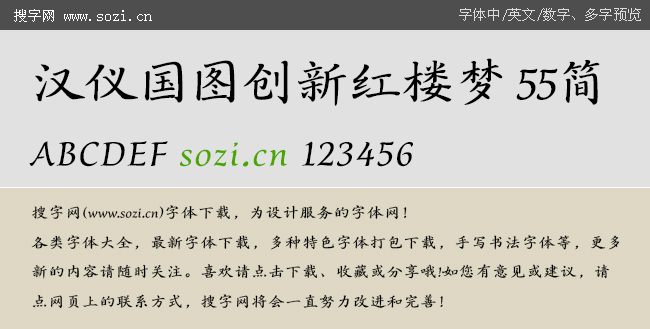
漢儀國圖創(chuàng)新紅樓夢 55簡
搜字網(wǎng)給大家提供一款漢儀國圖創(chuàng)新紅樓夢 55簡中文字體下載,漢儀國圖創(chuàng)新紅樓夢字體家族是一套藝術(shù)楷體字體,字體共擁有五款字重,字體簡潔大方,整體效果非常不錯。適用于畫冊設(shè)計(jì)、海報(bào)設(shè)計(jì)、包裝設(shè)計(jì)等場合使用。(本字體為個人非商用版,如需要商用請聯(lián)系漢儀公司購買版權(quán))
- 風(fēng)格類別: 楷體